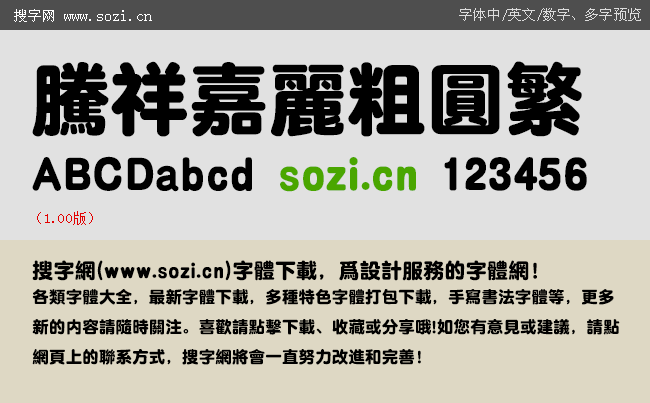
騰祥嘉麗粗圓繁
搜字網(wǎng)提供一款騰祥嘉麗粗圓繁字體下載,該字體每個漢字都經(jīng)過精心設(shè)計(jì),筆畫粗細(xì)均勻、結(jié)構(gòu)美觀。每個字的圓角、圓頭、勾形都極光潔、風(fēng)格統(tǒng)一,字形放大不變形,縮小顯示清晰,適用于樣本畫冊,報(bào)紙排版,網(wǎng)頁標(biāo)題等廣告設(shè)計(jì)應(yīng)用。